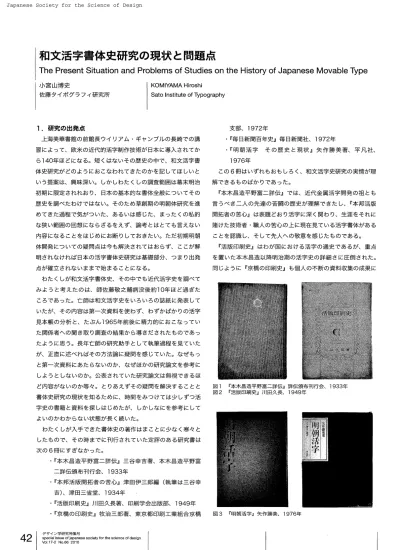
The
Present
Situation
and
Problems
of
Studies
on
’
the
History
of
Japanese
Movable
「
ype
和 文 活 字
書
体 史研 究
の
現 状
と
問 題
占
1
.
研 究
の出 発 点
上 海 美
華 書 館
の前館
長 ウ ィ リ ア ム・
ギャンブル の長 崎で の講
習
によ
っ て、
欧米
の近代 的 活 字制 作 技術
が 日本
に導
入 さ れて か ら140
年
ほどに な る。
短く は な い そ の歴史
の中
で、
和 文 活字 書
体 史
研究
が どのよ うにおこ なわ れて き たの か を記し てほし い と いう提案
は、
興 味 深い。 し か しわた くし の調査範
囲は幕末
明 治初期
に限 定
さ れ れおり
、 日本
の基 本 的
な書 体 全般
につ い て そ の 歴史を調べ た わ け で は な い。
そ の た め草
創 期の明朝
体 研究
を進 めて き た過 程
で気
がつ いた、
あるいは感
じた、
まっ た くの私 的
な狭
い範
囲の回想
にならざるをえず
、
論 考
と は と て も言えない 内容
に な る こ と を は じ め に お断り して お き た い。 た だ初 期 明朝
体 開発
につ い て の疑 問 点
は今
も解決
さ れて はおらず
、
こ こが解
明さ れ な け れば 日本
の活
字書 体 史
研 究は基 礎部
分、
つま り出
発点
が確
立され ない ままで始
ま る こ と に な る。わ た く しが
和 文
活字 書体 史
、
そ の中
で も近代 活 字 史
を調べて み よう と考
え た のは、
師 佐 藤 敬
之輔 病 没 後 約
10
年
ほ ど過
ぎ た ころ で あっ た。
亡師は和
文 活字 史
を い ろ い ろ の誌
紙に発 表し て いた が、
その内 容
は第
一
次資 料 を 使 わず
、
わ ず
か ば かり
の活 字
見本 帳
の分 析
と、
たぶ ん1965
年 前後
に精 力 的
に お こなっ て い た関 係者
への聞き取 り調査 の結 果か ら導
き だ さ れ た も のであ っ たよう に 思 う。 長年
亡師
の研 究 助
手と し て執筆
過程
を 見ていた が、
正直に述べ ればそ の方 法論
に疑 問を感じ て い た。
な ぜ もっ と第
一
次 資料
にあ
たらない のか、
な ぜほかの研 究 論 文
を参 考
に しようとしない の か。
公 表 さ れて い た研 究 論 文は無 視で き る ほ ど内 容
が ない のか等
々。
と り あえず
そ の疑 問
を解 決
すること と 書 体 史 研 究の現 状 を 知るた めに、
時 間 をみ つ けて は少
しずつ活 字 史の書 籍 と 資料
を探
し は じ め た が、
し か しな に を参 考
に して よい のか わ からない状
態 が長
く続
いた。わ た く し が入手でき た 書 体 史の
著 作
はまことに少
なく寒
々 と したもの で、
その時 まで に刊 行 さ れて いた定 評の ある研 究 書 は次
の6
冊にす ぎ
なかっ た。
・
『本 木 昌
造 平 野富
二詳 伝
』 三谷 幸 吉 著
、
本木
昌造
平 野富
二 詳 伝 頒 布 刊 行 会、
1933
年・
『本 邦 活 版 開 拓 者の苦 心』 津 田 伊三郎 編 (執 筆 は 三 谷 幸吉
)
、
津
田三省 堂
、
1934
年
・
『活 版 印刷 史
』川
田久
長著
、
印刷 学 会 出版 部
、
1949
年
・
『京 橋の印 刷 史 』 牧 治三郎 著、
東 京 都 印 刷工業 組 合 京 橋支 部
、
1972
年
・
『毎
日新
聞 百年 史
』毎
日新
聞社
、
1972
年
・
『明朝 活 字
その歴史
と現状
』矢 作 勝 美 著
、
平 凡社
、
1976
年
こ の
6
冊は いず
れ もおもし ろ く、
和 文
活字 史
研究
の実 情
が 理 解で き る も のばか りで あっ た。
『
本木 昌造 平
野富
二詳伝
』 では、
近 代 金
属活 字 開
発の祖
とも 言うべ ぎ 二人の先 達の苦 闘の 歴史が 理解
で き た し、
『本 邦 活 版開拓 者
の苦
心』 は表
題 どお り活 字
に深
く 関 わ り、
生涯
を それに賭
けた技術 者
・
職 人
の苦心
の上に現在
見て い る活 字 書体
が あ る こ と を認識
し、
そ して 先 人へ の敬 意
を感じ た も ので あ る。
『
活版 印刷 史
』 はわ
が 国 に おけ
る活 字
の 通史
であ
るが
、
重 点
を置い た本 木
昌造 以降
明 治 期の活字 史
の詳 細さ に 圧倒
さ れ た。
同じよ うに 『京橋
の印 刷 史
』 も個 入
の不断
の資 料収 集
の成
果 に 図1
『本 木 昌造平 野富二 詳伝 』 詳伝頒布刊 行 会、
1933
年 図2 『活 版 印刷 史 』 川田久長、
1949年 図3 『明朝 活 字 』 矢 作 勝美、
1976 年42
裏打
ち さ れ た広 範
囲な記述
に驚
い た。
京 橋
と い う狭
い一
地 域
の 印刷 史
であ る が、
実
は 明治
以降
の活字
に 深 くか か わっ てい るこ と を 知 った一
冊であっ た。
『毎 日 新 聞 百 年 史』 の 中 の 「技 術 編 は同 社の古 川 恒の執 筆だ が、
金 属 活 字で新 聞 印 刷 を 目 指 し た 毎 日新
聞草 創 期
の紙
面の分析 結
果 の 記述
は、
わ た く し の そ の 後 の 研 究 方 法の基 礎になっ て い る。
ま た亡 師と活 字につ い て 話し合 う厳
しい顔
の 「実
証主 義 者」
の面 影 が 忘 れ が たい。
こ の中でもっ と も
参
考になっ たのが 『明 朝 活 字』 であった。
現在
にっな
が る 日本の基 本書 体
で あ る 明朝 体
の誕 生と発達
過 程 を初めて詳 細に記述
し た 「労 作 」 で、一
般
的に研 究が進め られ て い る 印刷通 史
と は異 な
り、
明朝 体
という一
書体
に焦点
を あて 日本
の近 代 を そこから切 り 取 ろ うと いう もので、
こういう 研 究 の アプロー
チが ある の か と眼を見 張っ た 記 憶がいまも鮮 明 に残
っ て い る。 ま た 原寸
図 版の多
用と いう構 成
が本
文を読
み 進 め る う えで理 解しや す く、
配 慮の行 届いた編集
方 針であっ た。
これ ら
6
冊 を読
み比
べて いた 研究 初 心 者
のわ た く し に とっ て、
これまで の日 本の近 代 活 字 史 研 究は順 調に そ の歩み を進め て い る よ うに見 え た。2
.
既 存 研 究
の疑 問 点 (
1
)
され
るなか、
中
国人
によっ て独 自
の美
意 識と感 性で開 発 され て い く宋 朝 体と楷 書 体の多 様さを発掘し た 労 作であ る。
そ して多 く の 中 国 人 が 印 刷 事 業 に参
入 す ること で、
欧 米 人に よ る こ の分 野で の独 占状 態を崩 壊さ せ、
印 刷 技 術面
で も自
立し て い く様
子を描
い て い る。中
国は良
い研究者
を得 た とい えるだろう。
この と き 開 発 さ れ た 宋 朝 体 と揩 書 体の一
部 は、
昭 和IO
年 初 頭 日 本 人の手に よっ て密か に持ち出され、
無 断で複 製され 活 字 見 本 帳に自社
独 自の書 体
と して掲 載
さ れ続